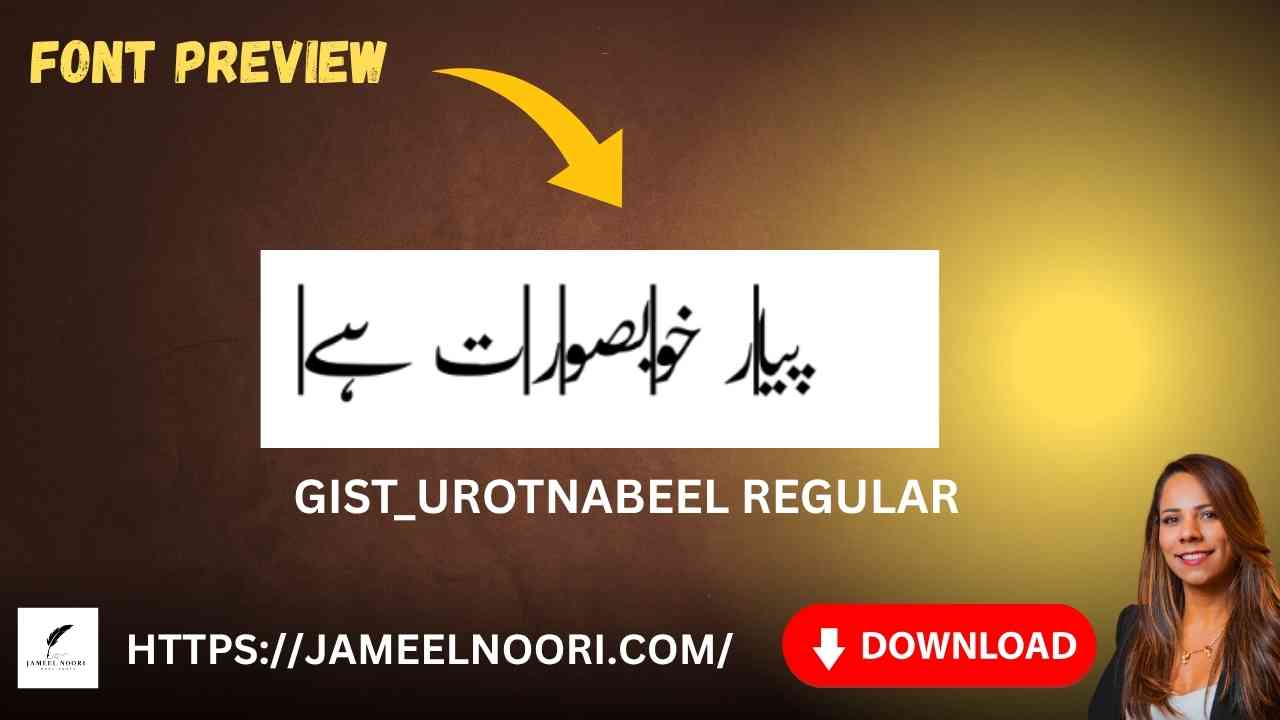
Download Urdu font GIST_UROTNabeel Regular – Latest Stylish Font
Agar aap Urdu me type karna pasand karte hain, to Download Urdu font GIST_UROTNabeel Regular aap ke liye ek best choice ho sakta hai. Yeh font un logon ke liye banaya gaya hai jo Urdu typing me stylish aur readable output chahte hain. Pakistan me kai log is font ko headlines, design projects, aur official documents ke liye use karte hain.
Download Urdu font GIST_UROTNabeel Regular ka Use Kahan Hota Hai?
Download Urdu font GIST_UROTNabeel Regular ka istemal kai jagahon par kiya jata hai, jaise:
- Government documents aur Urdu typing ke official kaam
- Graphic designing me headings aur quotes likhne ke liye
- Students apne Urdu assignments aur presentations ke liye
- Website content creators jese ke Lahore, Karachi aur Islamabad ke bloggers
Yeh font readability aur professional Urdu layout ke liye mashhoor hai.
Download Urdu font GIST_UROTNabeel Regular ki Key Features
Download Urdu font GIST_UROTNabeel Regular ke kuch powerful aur attractive features yeh hain:
- Stylish aur smooth Urdu characters
- Easy-to-read interface
Urdu font GIST_UROTNabeel Regular – Lahore aur Karachi ke Users ke Liye Best
Pakistan ke bade shehron jaise Lahore, Karachi, Islamabad me log Urdu typing ke liye Download Urdu font GIST_UROTNabeel Regular ko apna rahe hain. Iska design itna modern hai ke yeh font official aur creative dono purposes ke liye perfect fit hai.
Agar aap ek designer, student, ya office worker hain, to yeh font aap ke kaam ko aur bhi stylish aur readable bana dega.
What is GIST_UROTNabeel Regular font used for?
It is used for Urdu typing in documents, designs, and web content.
Is it suitable for graphic designers in Pakistan?
Absolutely! It’s widely used in Lahore and Karachi by designers.